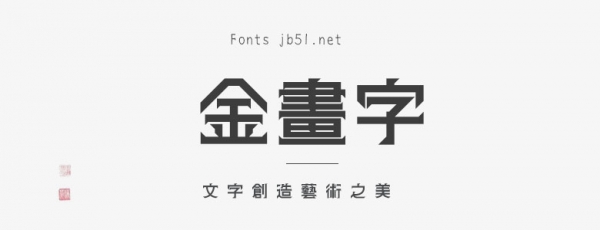
金畫字是一款45度筆畫加上直角三角形的襯飾日系免費(fèi)商用字體,適合用于一些平面文案、海報(bào)標(biāo)題、網(wǎng)頁廣告用字的編輯
作者從2021年到2022年10月制作的所有字體數(shù)據(jù)都丟失了,作者要求維修SSD,但被告知交貨日期未定且無法恢復(fù),因此放棄了字體的制作工作。
2022 年 11 月,我決定在短時(shí)間內(nèi)創(chuàng)建一個(gè)實(shí)用的字體,當(dāng)我看到 Twitter 上流行的“Seido”/ Daisuke Sato 一書的圖像時(shí),我想,“這個(gè)字符是 45 度嗎?”之后開始生產(chǎn)。我們感到欣慰的是,該版
本將于 2023 年 2 月完成。